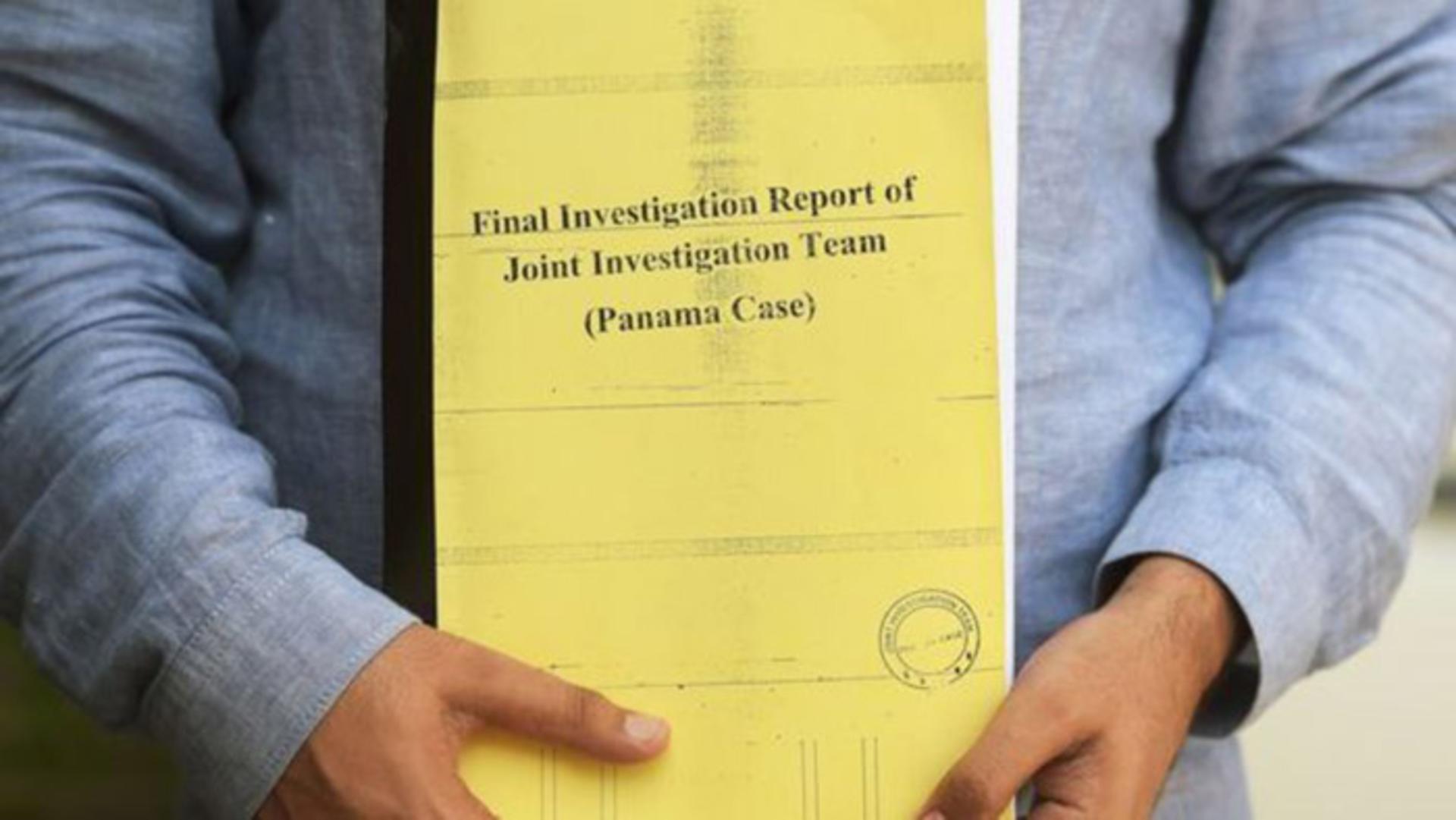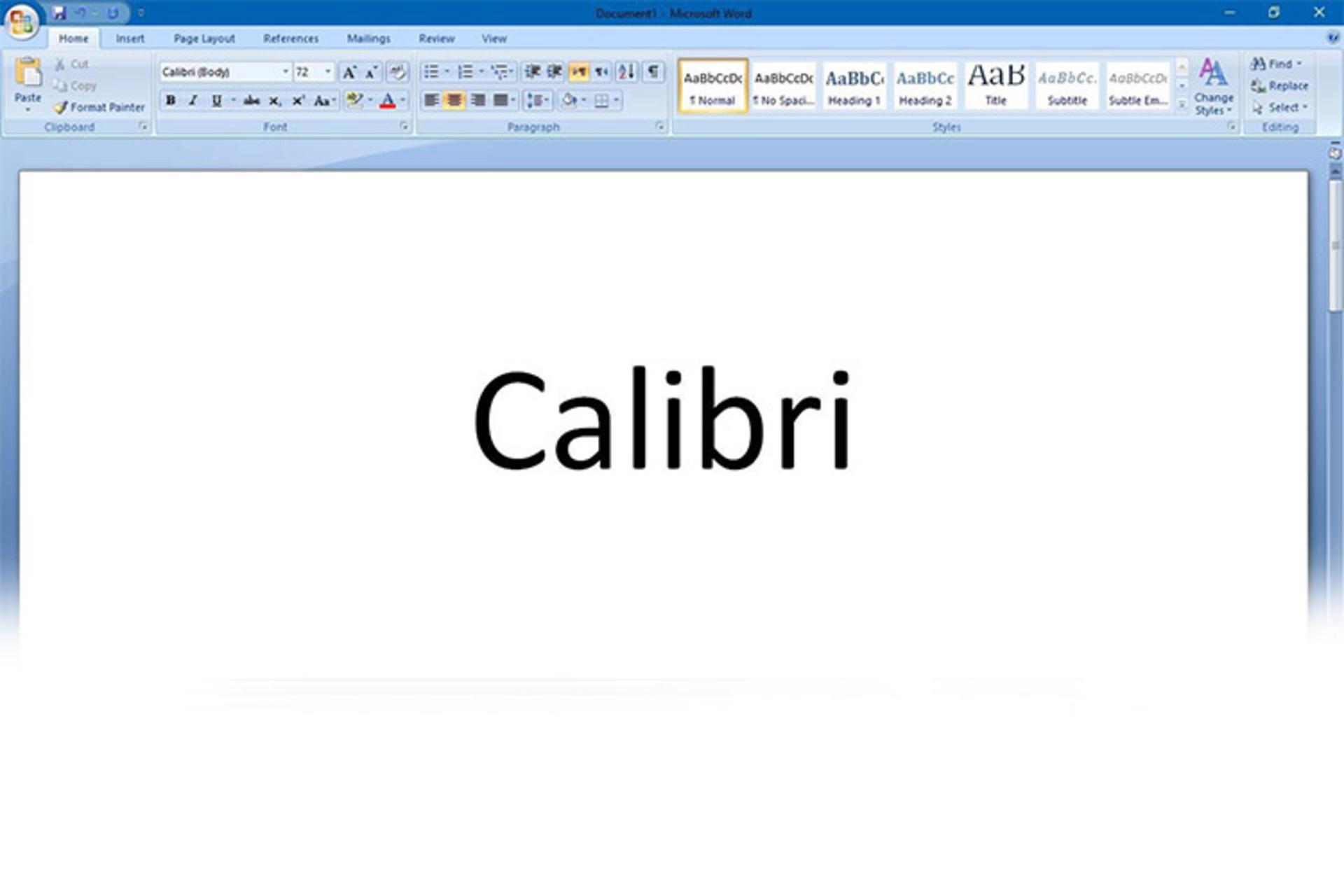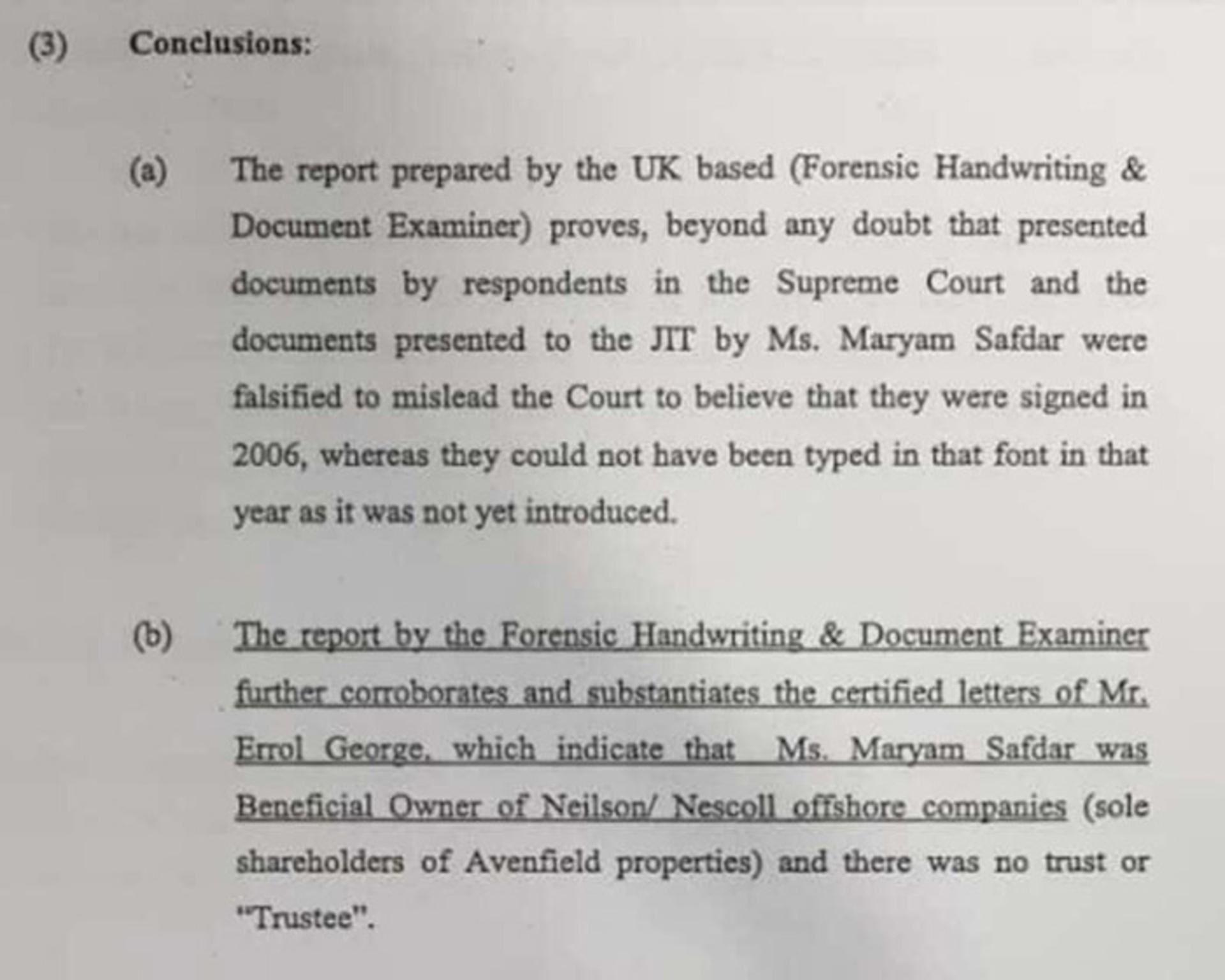
فونت مایکروسافت موجب عزل نخست وزیر پاکستان شد
فونت کالیبری مایکروسافت به‌عنوان مدرک در پرونده فساد مالی علیه نخست‌وزیر پاکستان مورد استفاده قرار گرفت که وی را ناچار به کناره‌گیری از سمتش کرد.
چند هفته پیش، فونت کالیبری مایکروسافت، به‌عنوان مدرک علیه نخست‌وزیر پاکستان، نواز شریف و خانواده‌اش در پرونده فساد مالی مورد استفاده قرار گرفت. در بخشی از حکم دادگاه دیوان عالی پاکستان اعلام شد که وی دیگر صلاحیت ماندن در مقامش را ندارد.
قضیه از کجا شروع شد؟
آوریل سال ۲۰۱۵، حدود ۱۱.۵ میلیون برگه سند از موسسه‌ی حقوقی موساک فونسکا در پاناما به بیرون درز کرد که نشان می‌داد چگونه شمار زیادی از ثروتمندترین و تاثیرگذارترین افراد در سراسر دنیا، با استفاده از گریزگاه‌های مالیاتی ثروت خود را مخفی کرده‌اند.
از زمان انتشار اسناد پاناما در سال ۲۰۱۵ به‌صورت ناشناس، تغییرات زیادی در وضعیت سیاسی بسیاری از کشورهای جهان صورت گرفته است. ازجمله کشور پاکستان که نام نخست‌وزیر و خانواده‌اش به همراه چند تن از اعضای کابینه‌ی دولت در این اسناد ذکر شده بود.
فونت کالیبری چه ارتباطی به این پرونده دارد؟
موضوع فونت کالیبری از زمانی آغاز شد که دختر نواز شریف، مریم نواز شریف، اسنادی را به‌منظور انکار هرگونه فساد در خانواده‌اش به دادگاه ارایه کرد. برای نوشتن اسناد مذکور در سال ۲۰۰۶، از فونت کالیبری استفاده شده بود و کاملاً قانونی به نظر می‌رسیدند. ولی بنا به اظهارات گروه تحقیقاتی، فونت کالیبری تا قبل از سال ۲۰۰۷ میلادی به‌طور رسمی و تجاری استفاده نمی‌شد؛ بنابراین تحقیقات گروه مسئول نشان داد فرم رسمی حقوقی با فونتی نوشته و چاپ‌ شده است که در آن زمان موجود نبود. فونت کالیبری، اوایل سال ۲۰۰۷ به‌صورت پیش‌فرض روی محصولات مختلف مایکروسافت عرضه عمومی شد.
اتهامات واردشده چه بودند؟
گروه تحقیقاتی دیوان عالی، متوجه اختلاف فاحش بین دارایی‌ و منابع مالی نواز شریف و خانواده او شد. علاوه بر این، آن‌ها به پنهان کردن و اعلام نکردن دارایی‌های واقعی خود باهدف توجیه اموال خانوادگی متهم شده‌اند.
رأی دیوان عالی چه بود؟
دیوان عالی کشور پاکستان بعد از چند هفته بررسی بیشتر، بالاخره رأی نهایی خود را اعلام کرد. طبق این رای نخست‌وزیر پاکستان به دلیل پرونده فساد مالی اعضای خانواده‌اش دیگر صلاحیت ماندن در مقامش را نداشت. وی همچنین از داشتن دفتر شخصی محروم شد. با توجه به طرح اتهامات زیاد علیه وی، خانواده و کابینه‌اش، باید همگی پاسخگوی سؤالات در دادگاه‎های بعدی باشند.
پیشینه نه‌چندان خوب نخست‌وزیر
این اولین بار نیست که نخست‌وزیر پاکستان در مدت ریاست ۵ ساله‌اش با مشکلات این‌چنینی دست و پنجه نرم می‌کند؛ وی پیش‌تر در سال‌های ۱۹۹۳ و ۱۹۹۹ هم از مقام خود برکنار شده بود. علاوه بر فونت کالیبری که نقش مهمی در محکومیت وی داشت، باید توجه داشت که شواهد دیگری مبنی بر تخلفات محرز نواز شریف و خانواده‌اش وجود دارند.